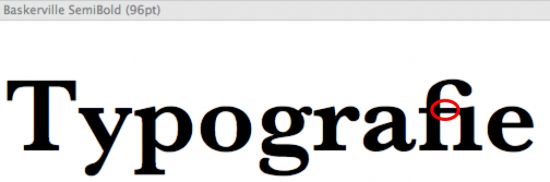
Suche alte Druckschrift (Pic inside)
ich brauche euren Rat. Und zwar suche ich die Schrift, die dieser Metall-Letter hinterlässt:
Gibt es das in digitaler Form?
Wenn nein: Gibt es etwas Ähnliches?
Und zwar suche ich die Schrift, die dieser Metall-Letter hinterlässt
Bevor uns der Bleisetzer-Georg erklärt, welche Schrift das jetzt genau ist, kann ich schon mal verraten, dass es sich um eine recht seltene Ligatur handelt, nämlich Lang-S-I, also »?i« innig verbunden. Da nur wenige digitale Schriften das lange S überhaupt enthalten und noch viel weniger auch die dazugehörigen Ligaturen, ist die Auswahl schon mal sehr eingeschränkt. Dann suchen wir eine Serifenschrift mit ziemlich robusten Serifen.
Pff, so auf den ersten Blick finde ich da nichts, tut mir leid.
Die Ligaturen sind nicht unbedingt notwendig.
Wenn die Schrift ähnlich...öhm...ge"stylt" ist, ist das auch okay
ja, das ist die "Lang-s/i"-Ligatur einer halbfetten Antiqua.
Nur anhand dieser Ligatur ist die Schrift aber nicht zu klassifizieren. Ich brauche dazu ein paar Versalien und Ziffern. Ideal: A, M, Q, R, 1, 7, 0. So etwas in der Art.
Ansonsten hatten so gut wie alle Antiqua- und Grotesk-Schriften, die vor dem Krieg gegossen wurden, das Lang-s - natürlich auch in den entsprechenden Ligaturen.
Hier z.B. die Genzsch Antiqua (das ist aber nicht die, die Du hier zeigst):
Ob die Ligaturen in die Digitalisierungen übernommen wurde, entzieht sich meiner Kenntnis. Das können Dir die feinen Herren mit den sauberen Fingernägeln hier sicher eher sagen.
Wofür brauchst Du das denn?
Vielleicht kann man Dir dann besser raten.
Die Adobe Caslon Pro und die Adobe Jenson Pro haben auch das ſ (Lang-s) und die Ligaturen.
Ich brauche die Schrift, um aus dem "fi" ein "Typografie" zu basteln.
Ach herrje! Dann nimm doch einfach ein »?« für die Typogra?e. Eine F-I-Ligatur also. Die ist in fast allen digitalen Schriften enthalten. Schau einfach mal in den Sonderzeichenbereich.
Hmpff ... ich sehe gerade, dass in meinem Beitrag die F-I-Ligatur nicht richtig kodiert bei mir ankommt. Sicherheitshalber schicke ich also mal ein Bild mit um zu zeigen, was ich meine. Beachte bitte besonders die Fortsetzung des Striches rechts vom Stamm des kleinen F, der beim langen S fehlt:
Ich glaube, du hast mich missverstanden...so schlimm ist es nicht :D
Bei genau dem Bild, das im Eingangspost steht, will ich "Typogra" und "e" hinzufügen...
Ich kann in Photoshop zwar ein wenig herumtricksen, aber eine Ähnlichkeit muss schon sein ;)
Aus dem "s" ein "f" zu machen dürfte nicht das Problem darstellen :roll:
Also Antiqua soll es sein...?